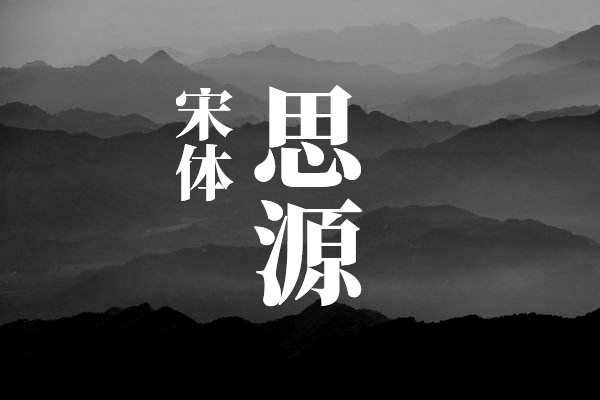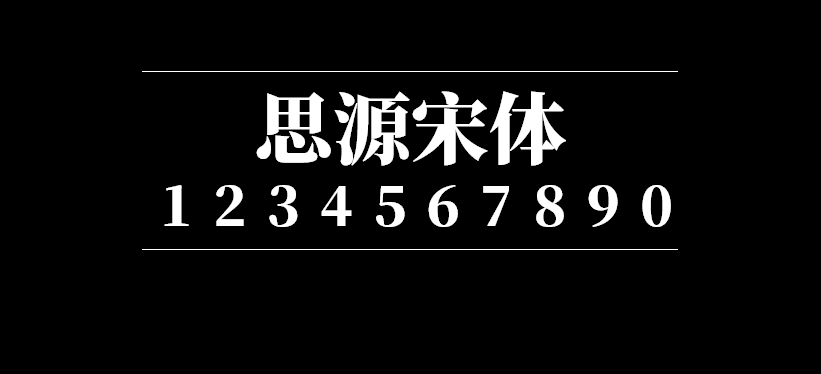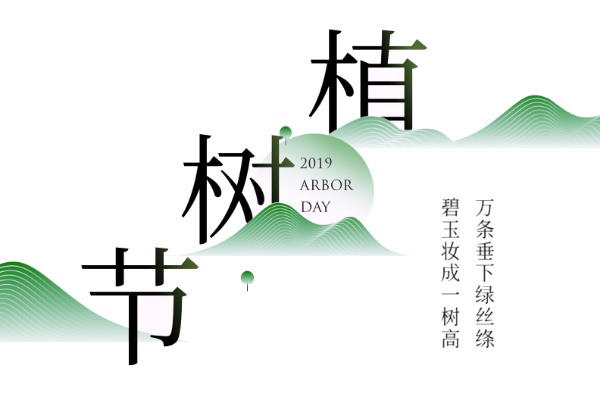
思源宋体-简体中文版
谷歌联合Adobe发布的全新开源字体——思源宋体(Source Han Serif),支持四种不同的东亚语言——简体中文、繁体中文、日文和韩文,同时还提供七种字体粗细形式的共65,535个字形(OpenType 格式支持的最大上限),以保证视觉审美上的一致性,同时可以满足各种不同的排版需求。 关于这4种语言的字形,看似有些是相同的中文字体,实际上可能有多达四个区域差异化的字形设计。思源宋体涵盖所有这些字形变体并且精心地设计了这些区域化字形。